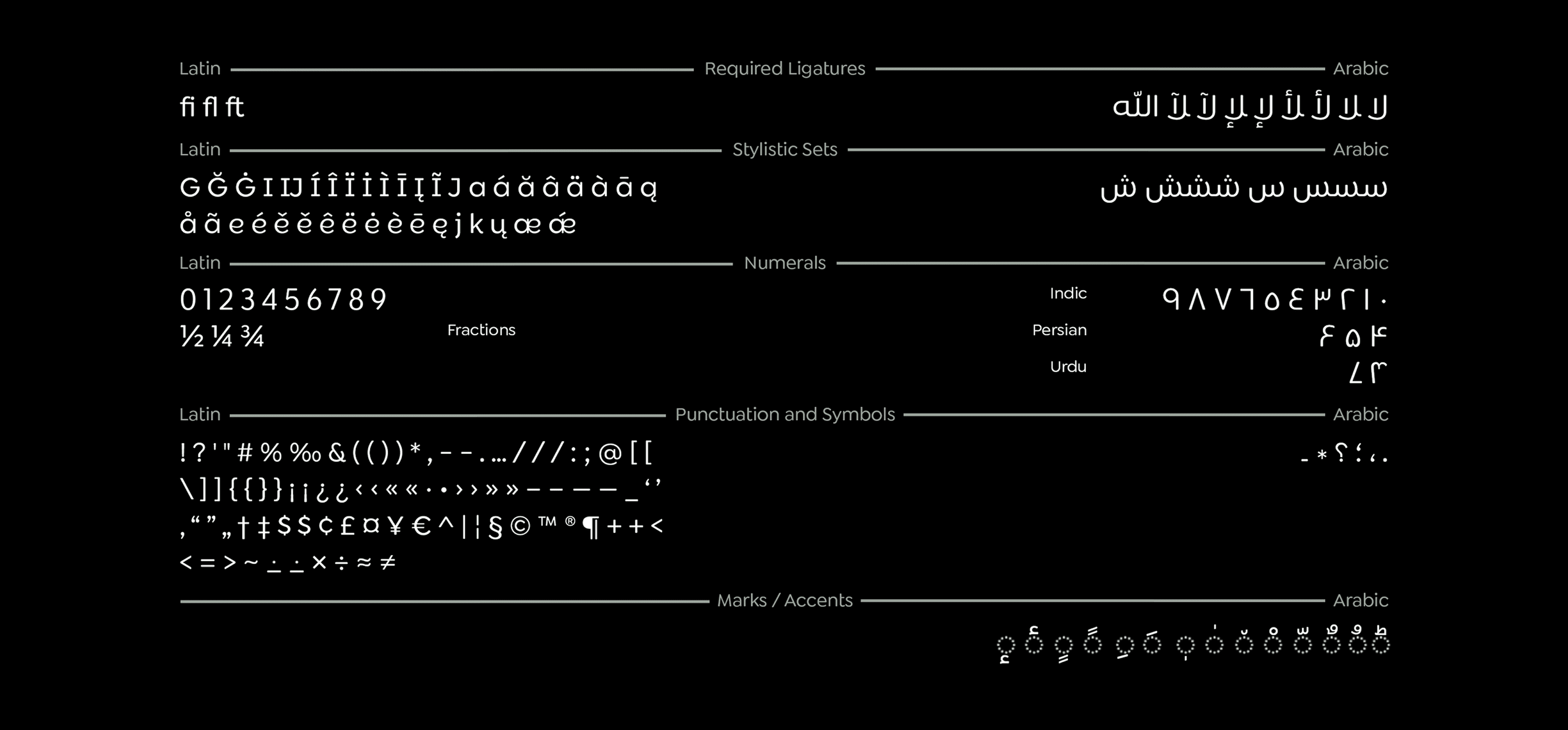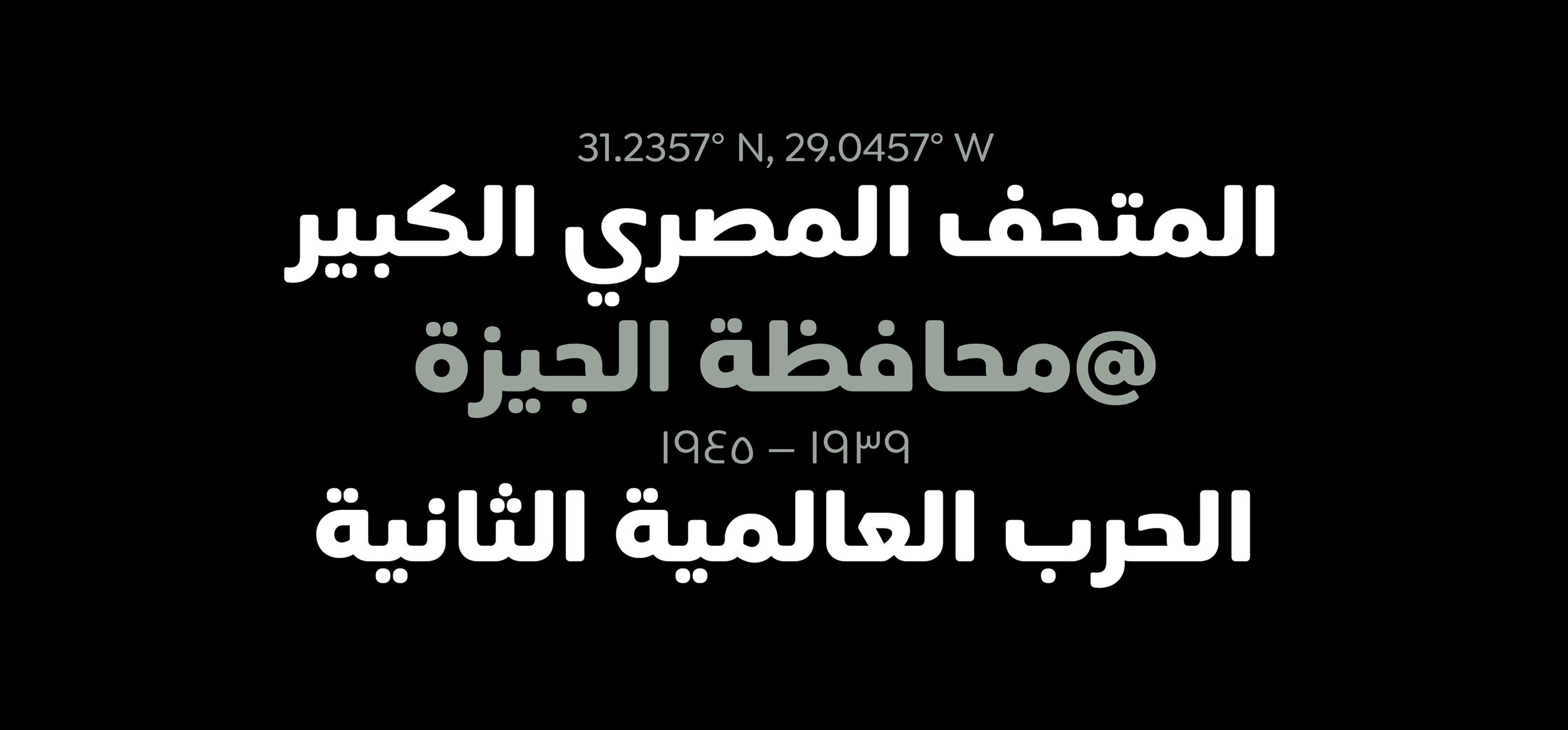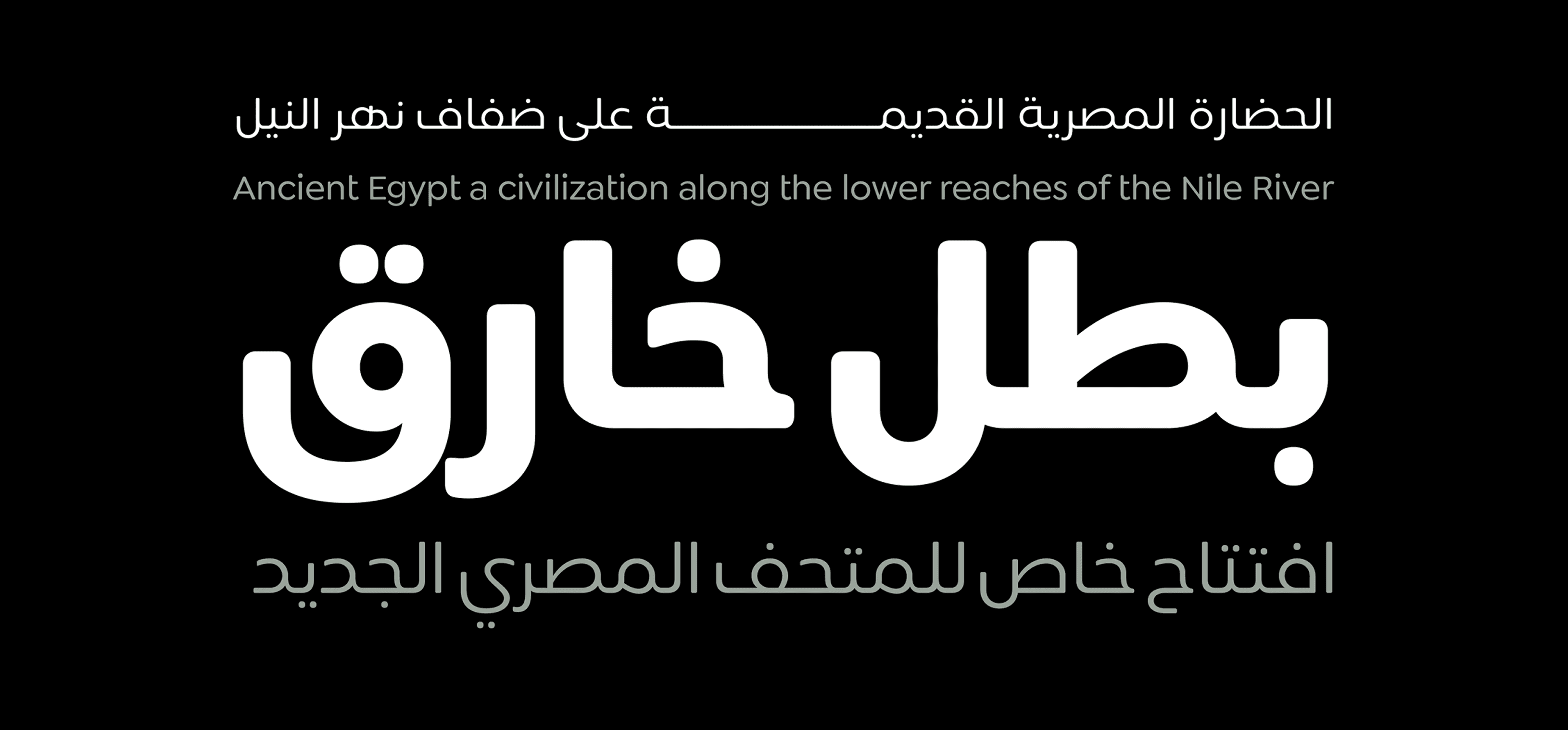
خط Siwa – Siwa Arabic Font Family
تم تصميم عائلة خط Siwa Arabic بواسطة عبده محمد وإبراهيم حمدي، ونُشرت من قبل Protype.
تتكوّن العائلة من 9 أنماط متنوعة، مما يمنح المصممين خيارات واسعة لتوظيف الخط في مشاريع مختلفة، بدءًا من العناوين الجريئة وصولًا إلى النصوص التفصيلية.
يتميز الخط بتوازن بصري مدروس، ودقة في التناسق بين الحروف، مما يجعله مناسبًا للطباعة الحديثة والتصميمات الإبداعية التي تتطلب وضوحًا وأناقة في آنٍ واحد.
مناسب للعربية والفارسية والأردية، مع دعم كامل للغات التي تستخدم الحرف العربي.